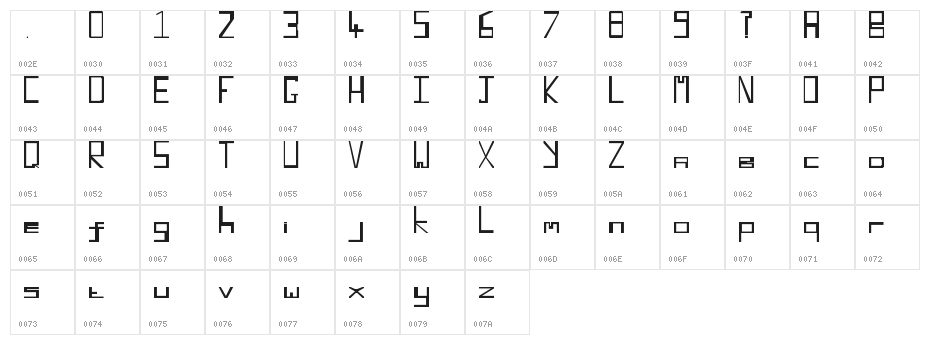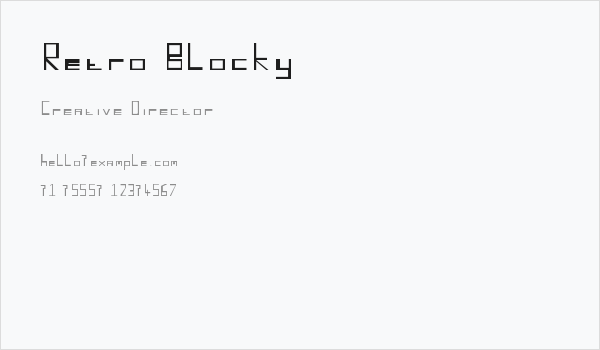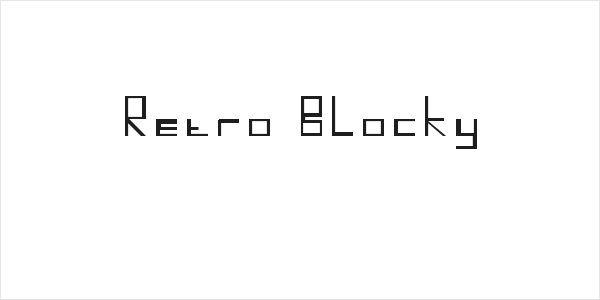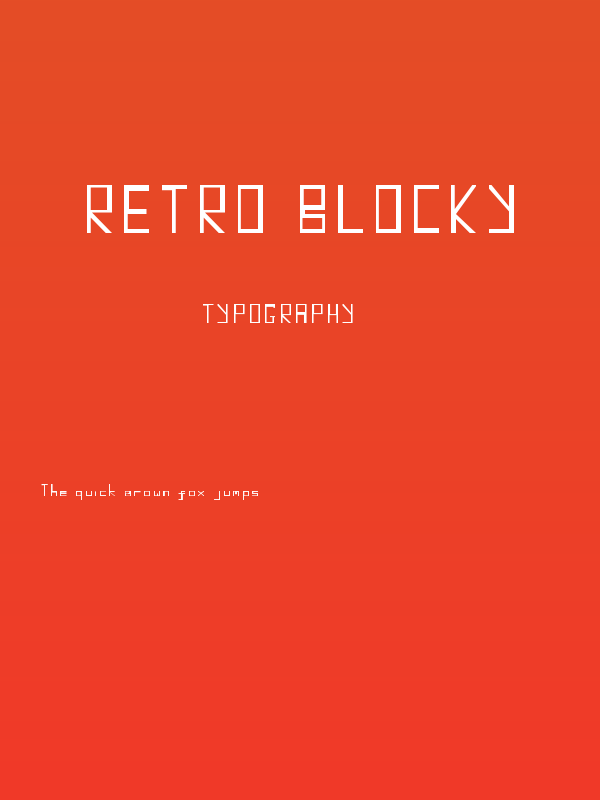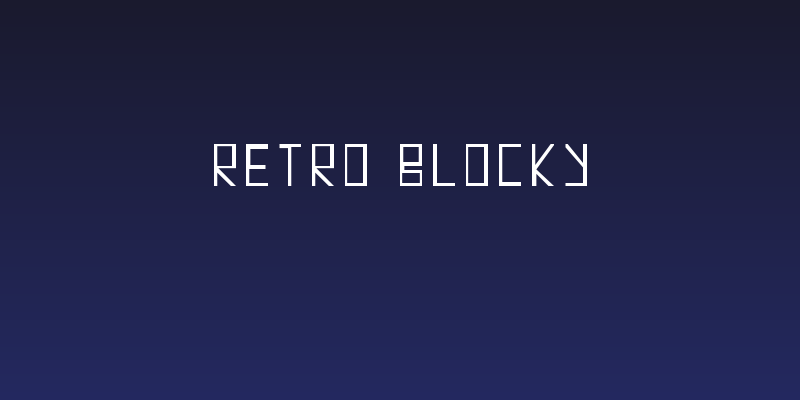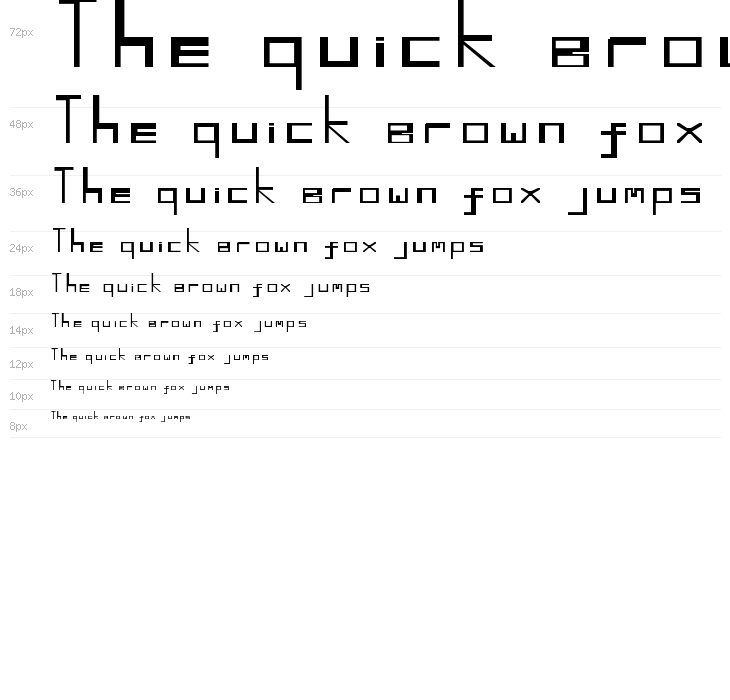
Retro Blocky Font
| Stile generale | Retro |
| Progetti proposti | Ideal for retro-themed designs, tech-inspired branding, video game graphics, and digital art projects. |